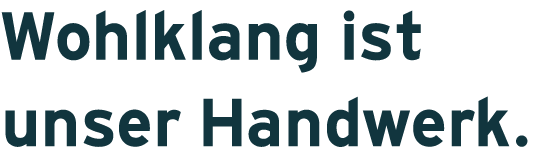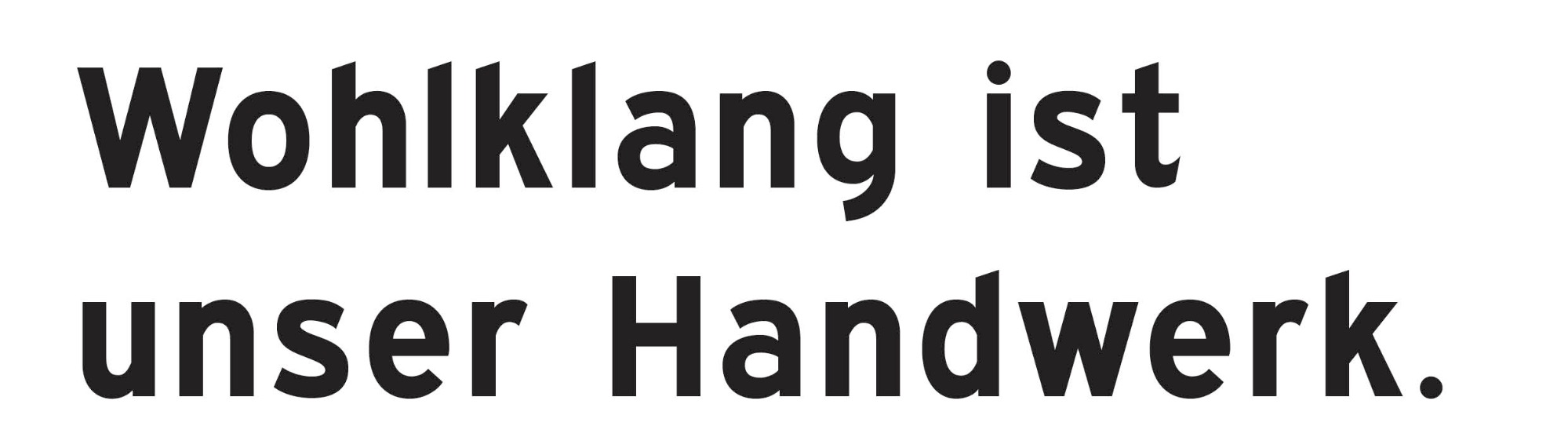
Suche Fontnamen von südeuropäischen Autobahnschildern
ich suche einen Font, der auf meiner Webiste www.eufoniker.de im Einsatz ist. Entstanden ist die Webseite im Januar 2020 in Düsseldorf. Möglicherweise aus Photoshop. Mir liegt nur die Info vor,  dass diese Schrift für Autobahnschilder in Italien genutzt wird. Könnt ihr weiterhelfen?
Lieber Ralf, ich habe von einer Grafikerin die Info bekommen, dass es sich hierbei um "Hit the Road" handelt. Sie ist etwas fetter als die Interstate.
Ja, das scheint die Gleiche zu sein die in der Font-Library vorkommt, heißt genauso und die Herstellerfoundry ist auch die Selbe.
In der Sammlung sind 28 Schnitte.
Bei meinem Beispiel, das ich nachgesetzt habe, musste ich die Schrift sperren.
Steffi, die den Strang ins Leben gerufen hat, schrieb ja, daß es eine Verkehrsschrift sein soll, die in Italien genutzt wird. Auf der Herstellerwebseite steht:
Expressway is a sans-serif font family inspired by the U.S. Department of Transportation’s FHWA Series of Standard Alphabets, also known as Highway Gothic. Since the middle of the twentieth Century, it’s the font most used on road signs in the United States, Canada, Mexico, Australia, Turkey, Spain, Venezuela, the Netherlands, Brazil, Argentina, Taiwan, Malaysia, Indonesia, India, Mongolia and New Zealand.